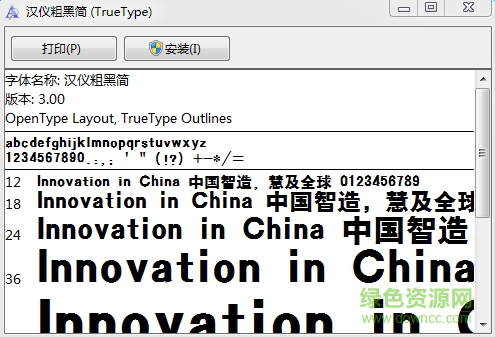
hyb9gj字體免費
hyb9gj字體免費版是一款使用范圍非常廣泛的字體哦,這類字體也是屬于漢儀字體中的一種,漢儀粗黑簡體,字形方正,非常美觀,感興趣的朋友趕緊來綠色資源網(wǎng)下載吧!
hyb9gj字體介紹
今天小編為你帶來hyb9gj字體。這個字體看著有點像粗體,顯得比較圓潤,非常適合廣告設(shè)計、平面設(shè)計、印刷包裝、正文標(biāo)題等人員使用。